Wie man eine handschriftliche Schrift erstellt
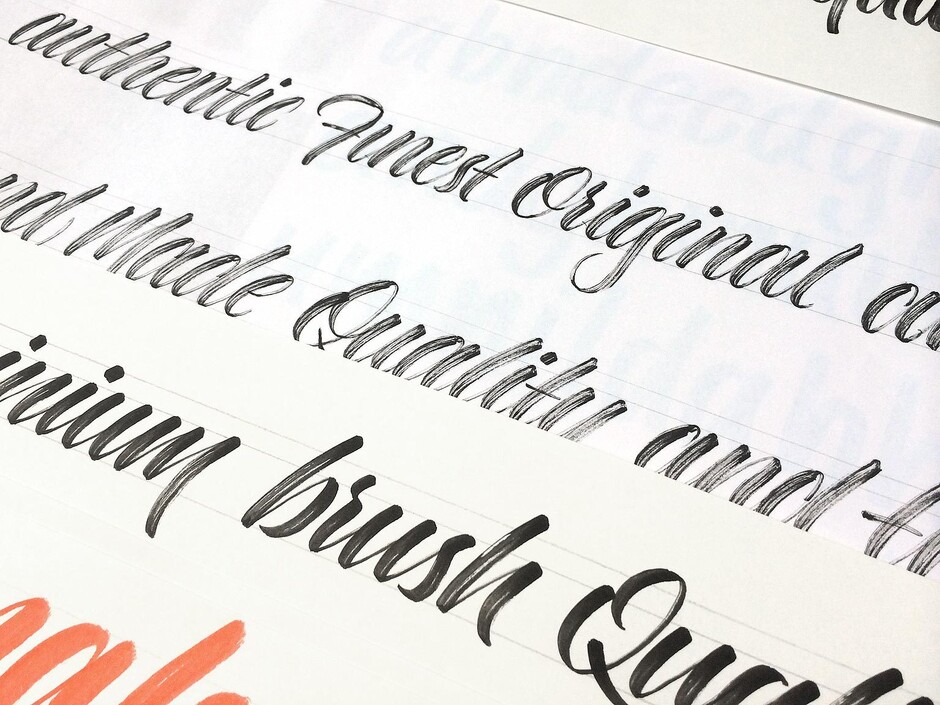
Wie man eine handschriftliche Schrift erstellt
FS Shepton® ist die erste Veröffentlichung des Fontsmith-Designers Andy Lethbrige, auf den Jason aufmerksam wurde, nachdem er seine exquisiten Handletterings auf Instagram und später in seiner Diplomausstellung gesehen hatte. Für seinen ersten Auftrag bat Jason Andy, mit einer Reihe von Medien zu experimentieren und eine Kollektion von drei Alphabeten mit ähnlichem Charakter, aber sehr unterschiedlicher Textur und Stil zu entwickeln.
Die meisten "handgeschriebenen" Schriften werden vollständig digital erstellt, nicht so FS Shepton. Jason und Andy wollten von Anfang an etwas schaffen, das zu 100 % handgezeichnet und absichtlich unvollkommen ist, mit der Art von uneinheitlichen, organischen Formen und Texturen, die man in einem Feinkostladen oder Gemüseladen sehen könnte.
Andys erste Station war der Kunstladen, "um mich mit Papier und Werkzeugen einzudecken, mit denen ich experimentieren konnte. Die ersten Wochen verbrachte ich damit, verschiedene Stifte und Werkzeuge auf unterschiedlichen Papieren und Oberflächen auszuprobieren. Ich musste mir überlegen, wie sich jede Stil und jede Textur auf dem Bildschirm und in der Schrift auswirken würde.
"Sie sind nicht perfekt - genau wie echte Handschrift haben sie Macken und Ungereimtheiten, weil sie geschrieben und nicht entworfen sind. Ich denke, das macht ihren Charakter aus und hilft ihnen, sich von der Masse abzuheben.
FS Shepton Regular, gezeichnet mit einem nassen Pinselstift, ist solide mit einer rauen Außenkante und einem lässigen, aber kontrollierten Gefühl.
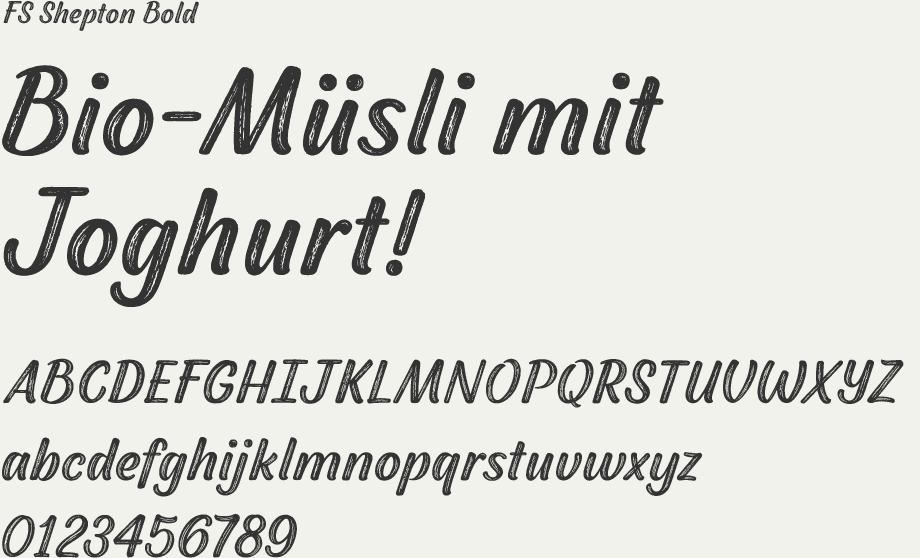
Die FS Shepton Bold, die mit einem breiteren, lockeren Pinselstift gezeichnet wurde, hat in der Mitte ihrer breiten Striche eine holzige Maserung und eine größere Festigkeit, wo sich der Pinsel langsamer bewegt. Im Gegensatz dazu werden die Buchstabenformen der konventionellen Schrift Fonts einfach digital gemästet, um schwerere Striche zu erzeugen.
Der trockene Pinsel, mit dem FS Shepton Light erstellt wurde, verleiht ihm mehr innere Textur und eine formalere, schräge, kalligrafische Stil.
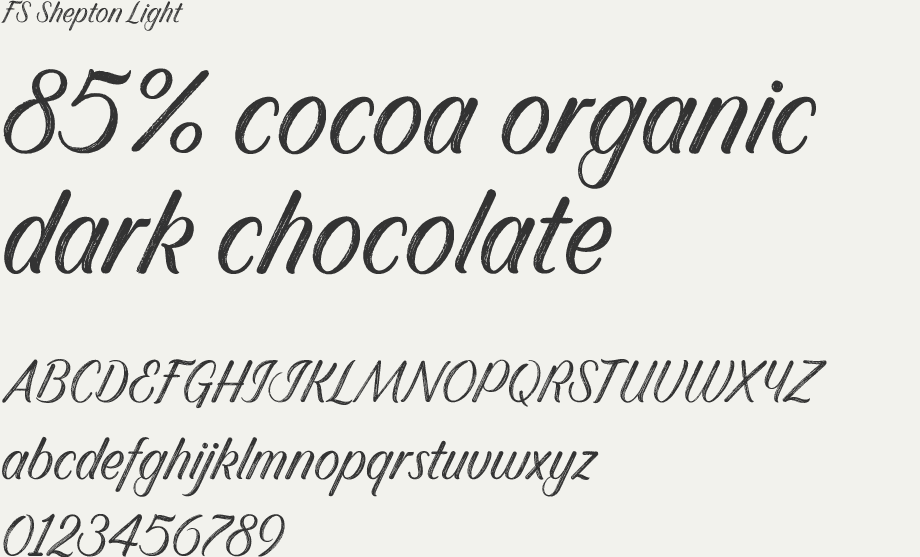
Das Schwierigste, so Andy, war "die Erstellung vollständiger und einheitlicher Zeichensätze. Selbst ein und dasselbe Werkzeug kann viele Variationen erzeugen - ein und derselbe Pinselstift gab mir unterschiedliche Texturen, je nachdem, wie viel Tinte er noch hatte.
"Die Digitalisierung der strukturierten Kalligrafie war auch deshalb schwierig, weil ich die ursprüngliche Textur und Form der Buchstaben beibehalten, aber die Daten minimieren und eine Font erstellen musste, die technisch funktioniert.
"Trotz oder vielleicht gerade wegen der vielen Herausforderungen bin ich stolz auf FS Shepton. Obwohl jedes Alphabet sehr unterschiedlich ist, haben sie alle einen Hauch voneinander, weil sie von derselben Hand geschaffen wurden."